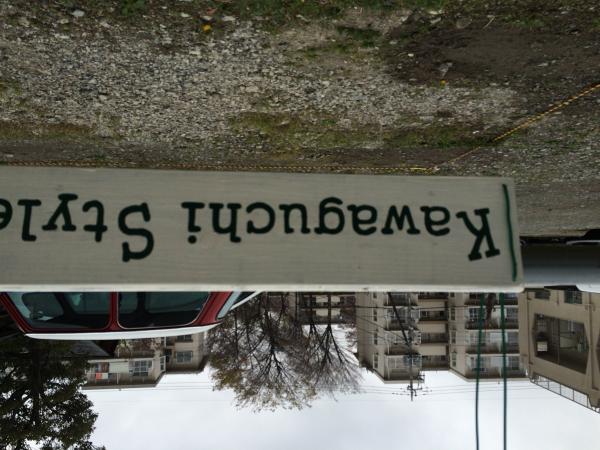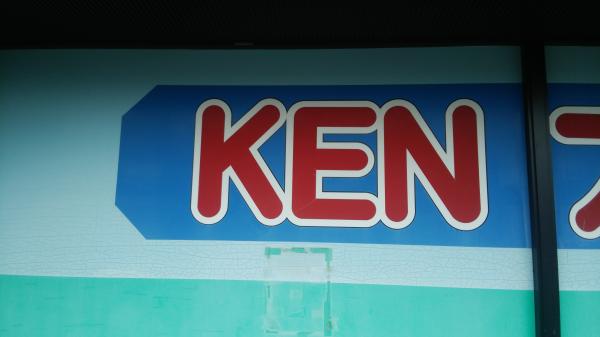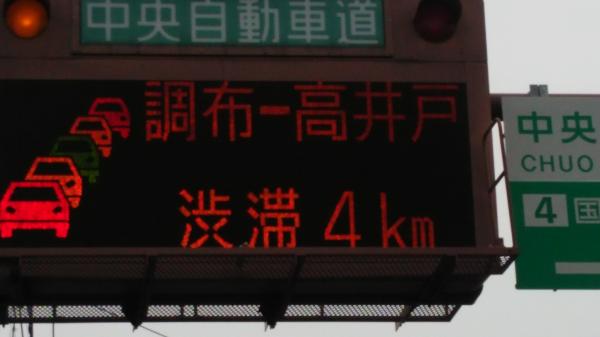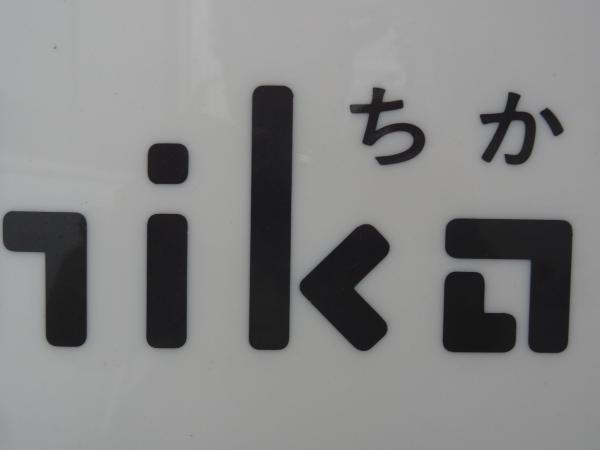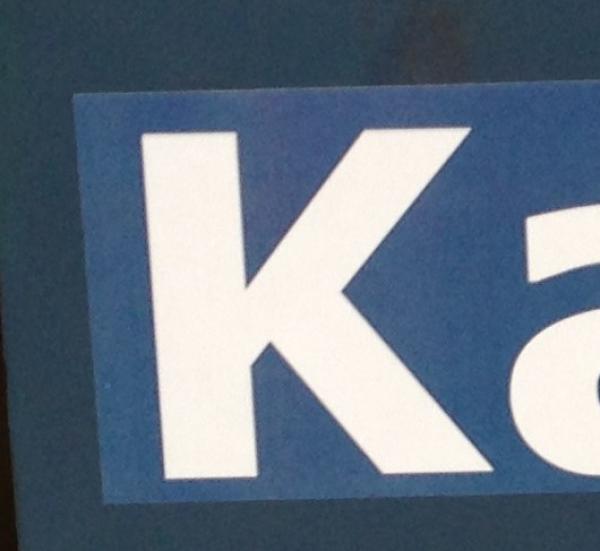
美味しいコーヒー屋さんです
国立はぴすぽ
谷保の近くの地下にある、暮らしに近いものづくりコミュニティースペース。
あまり見たくない文字。谷保っぽさはあまりないですね…
よく見るロゴですが、よく見ると、いつも見てるロゴと違うように見えました。
谷保駅前の本屋。店主さんの趣味と合わないのか、ちょうど品切れているのか分からないが、目当ての本がないことが多い。
傾いたK